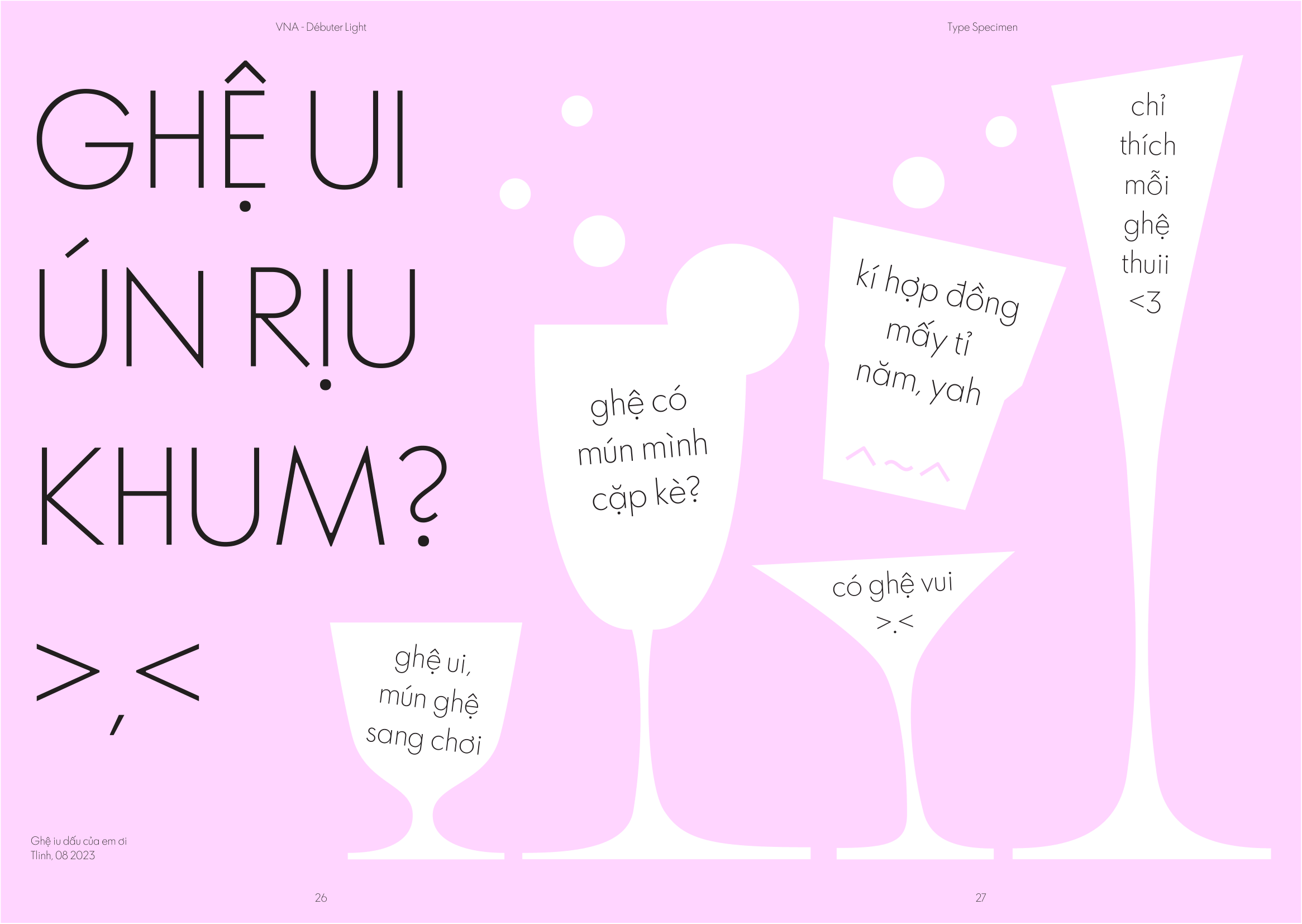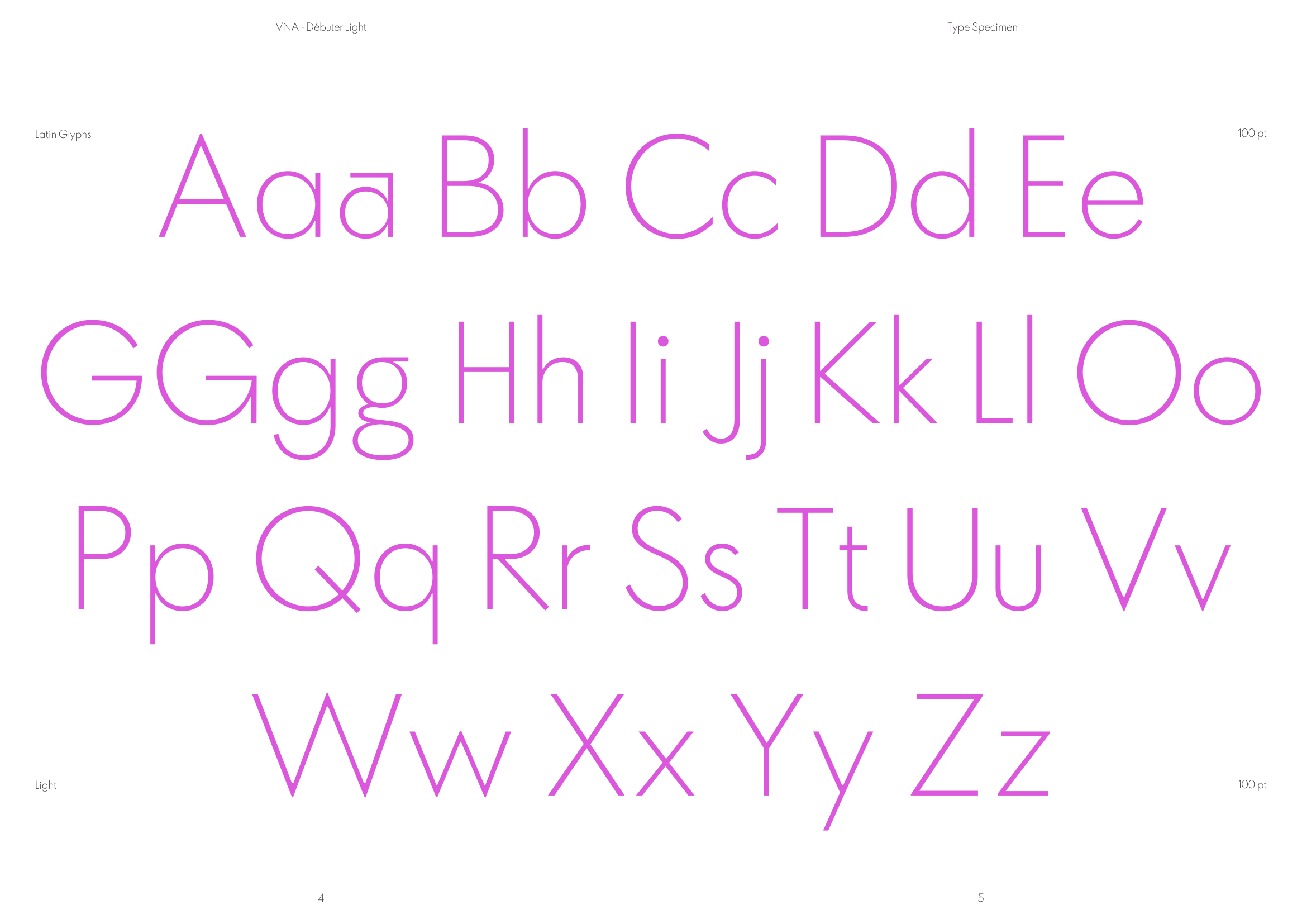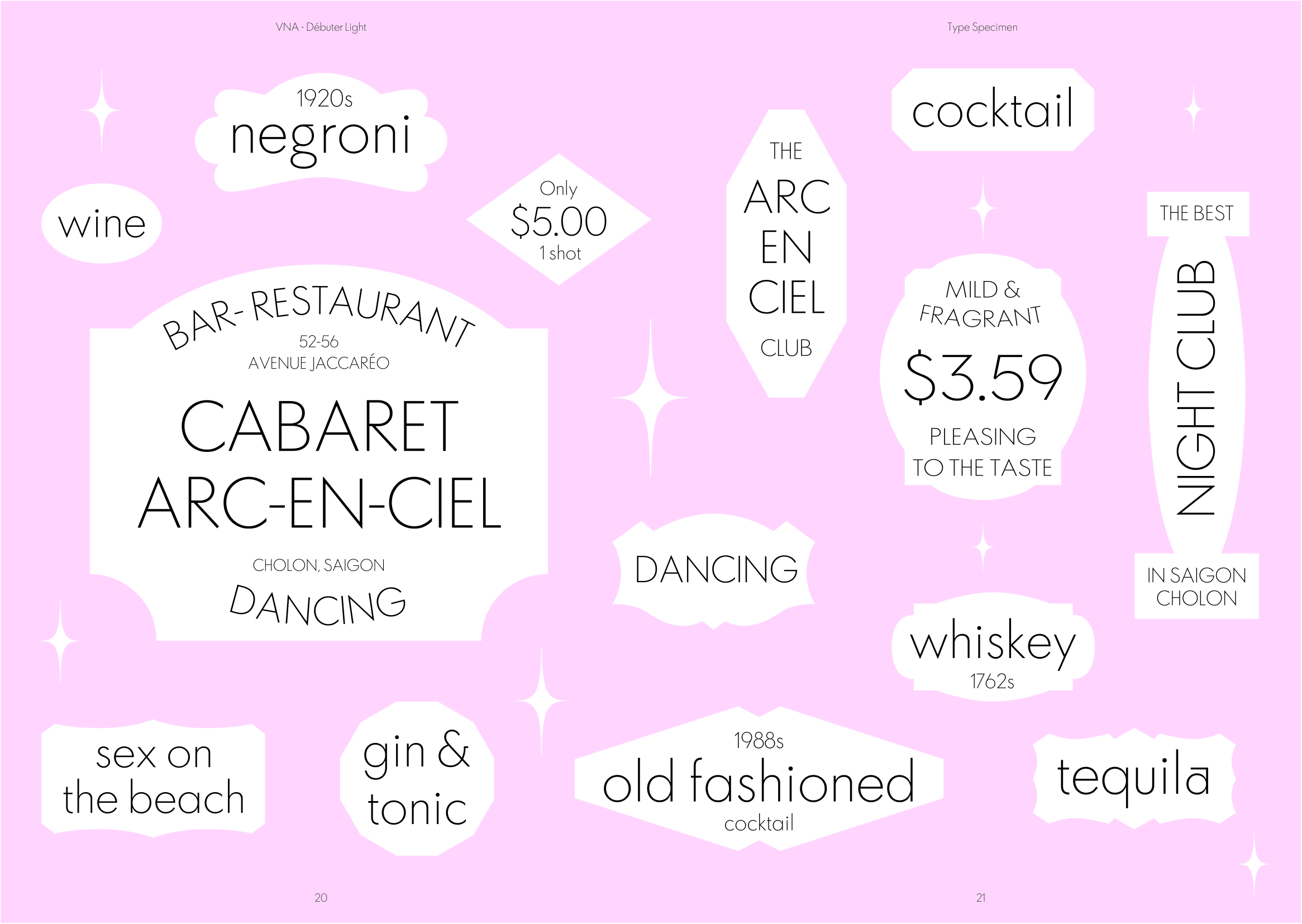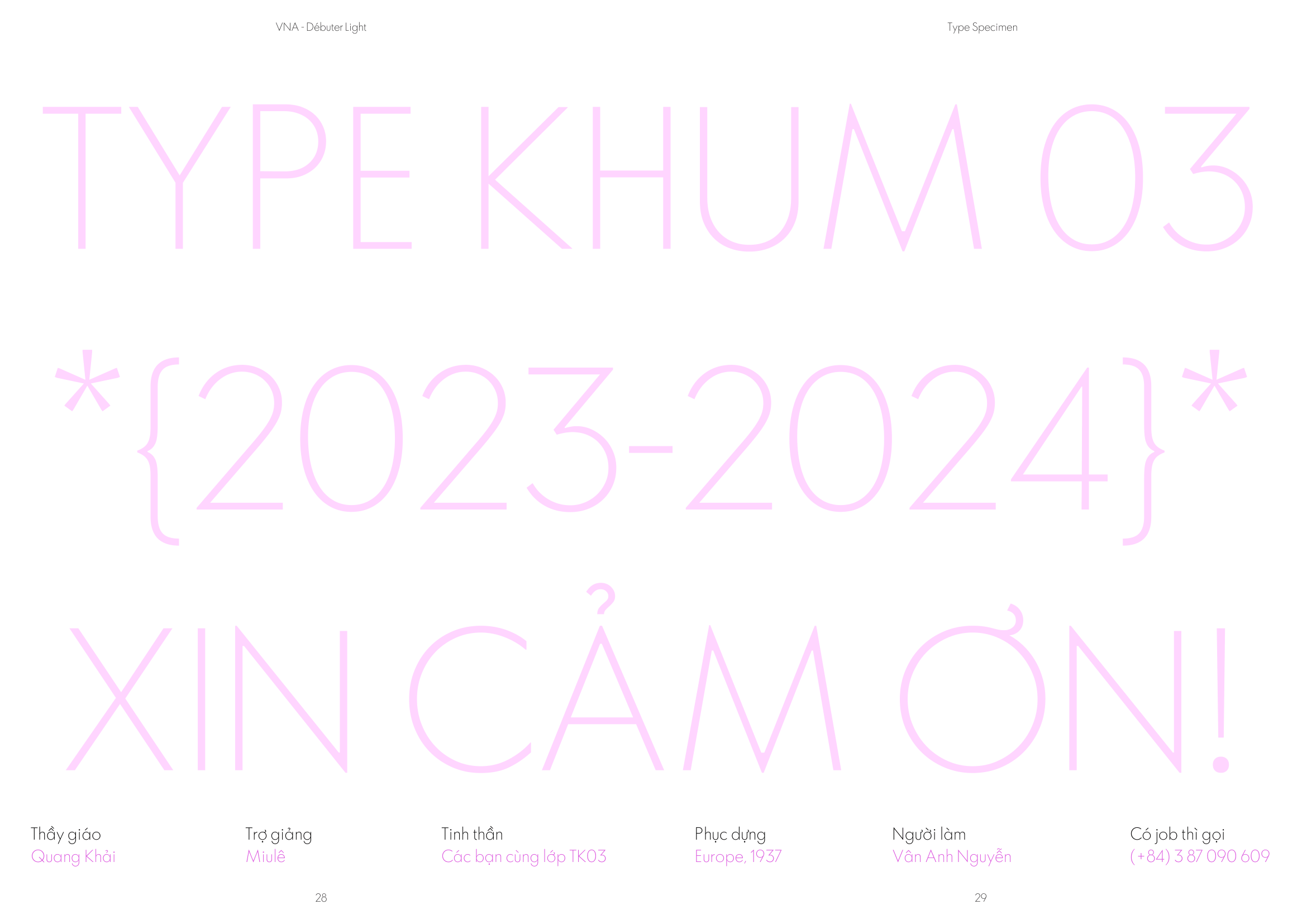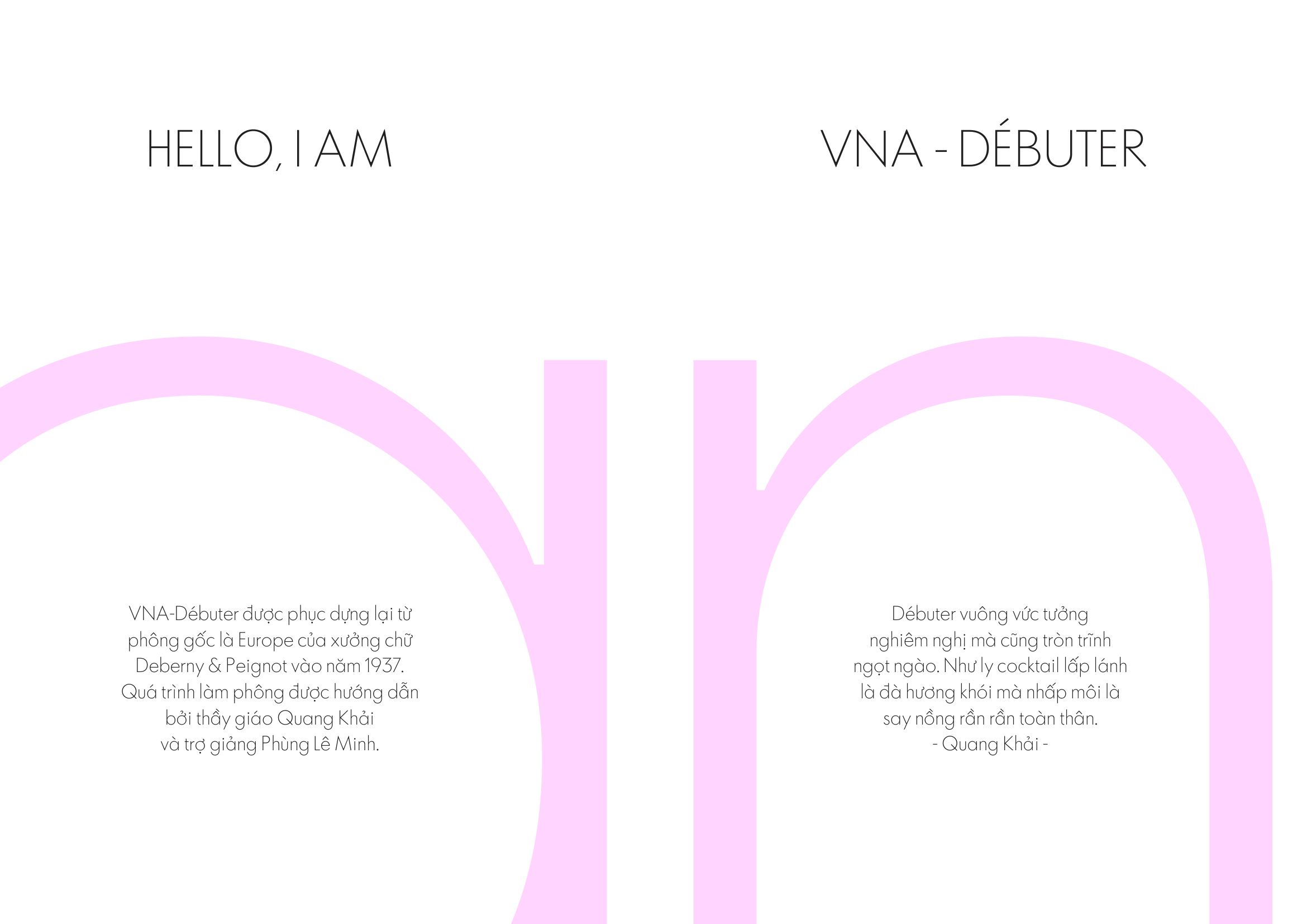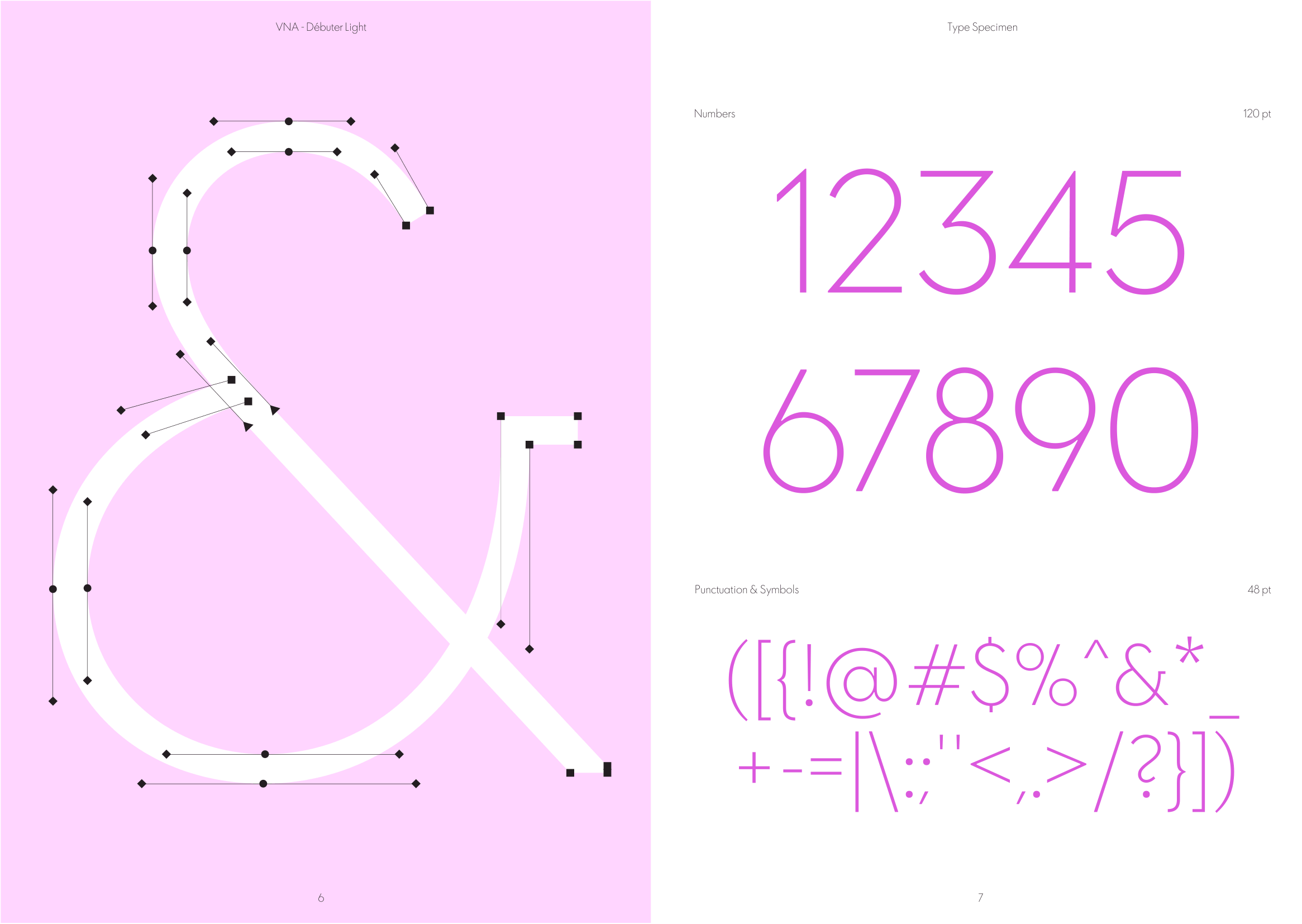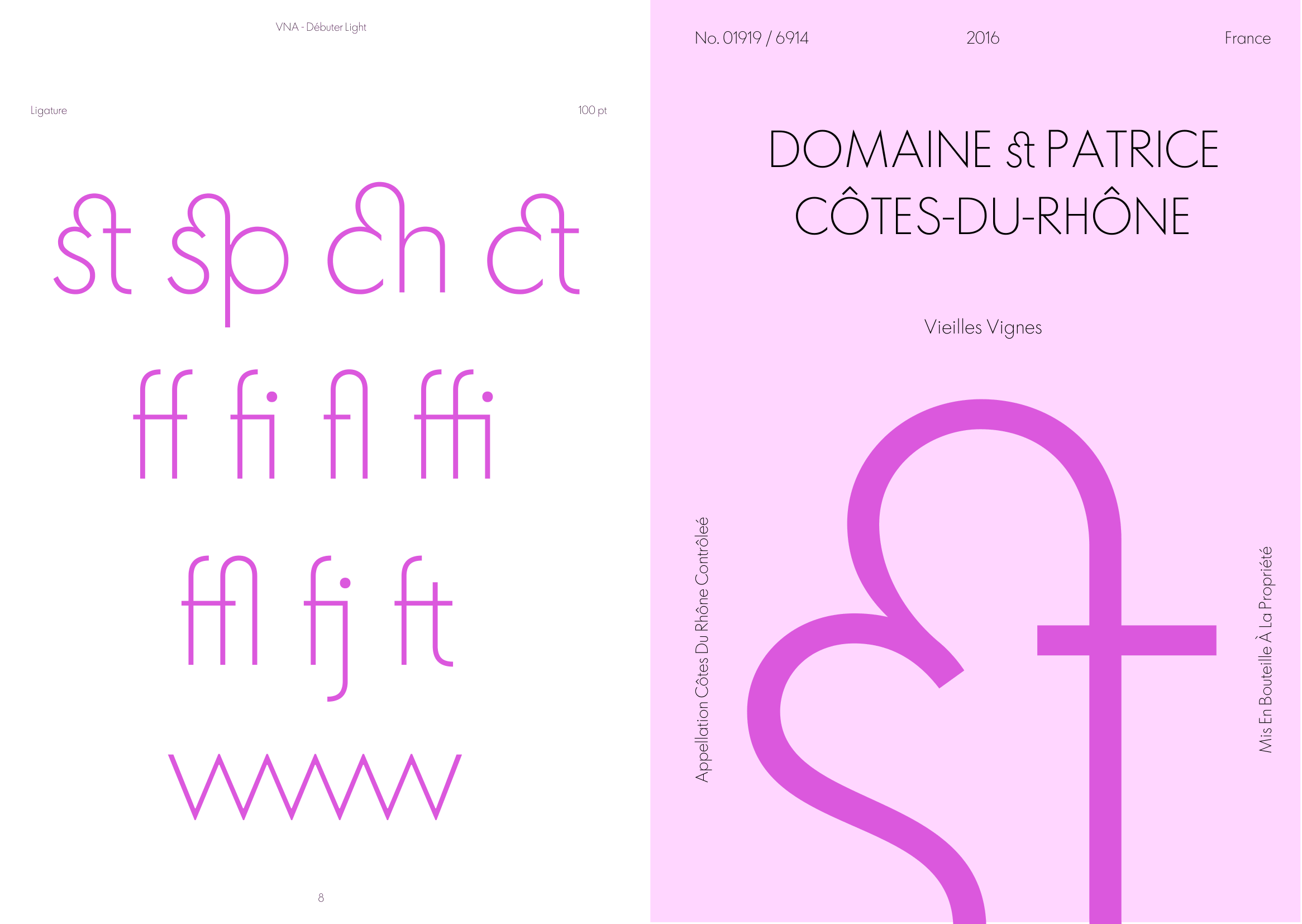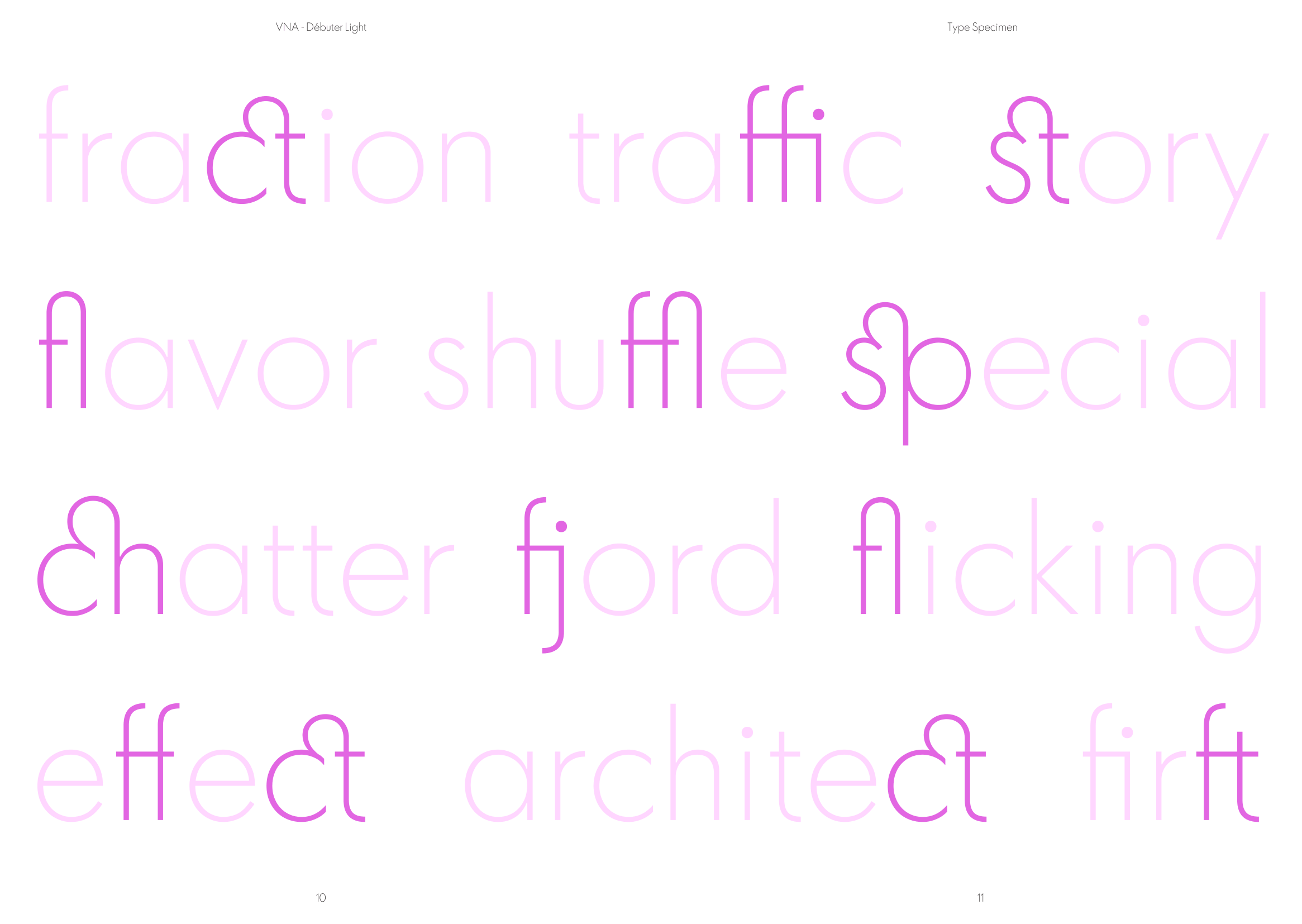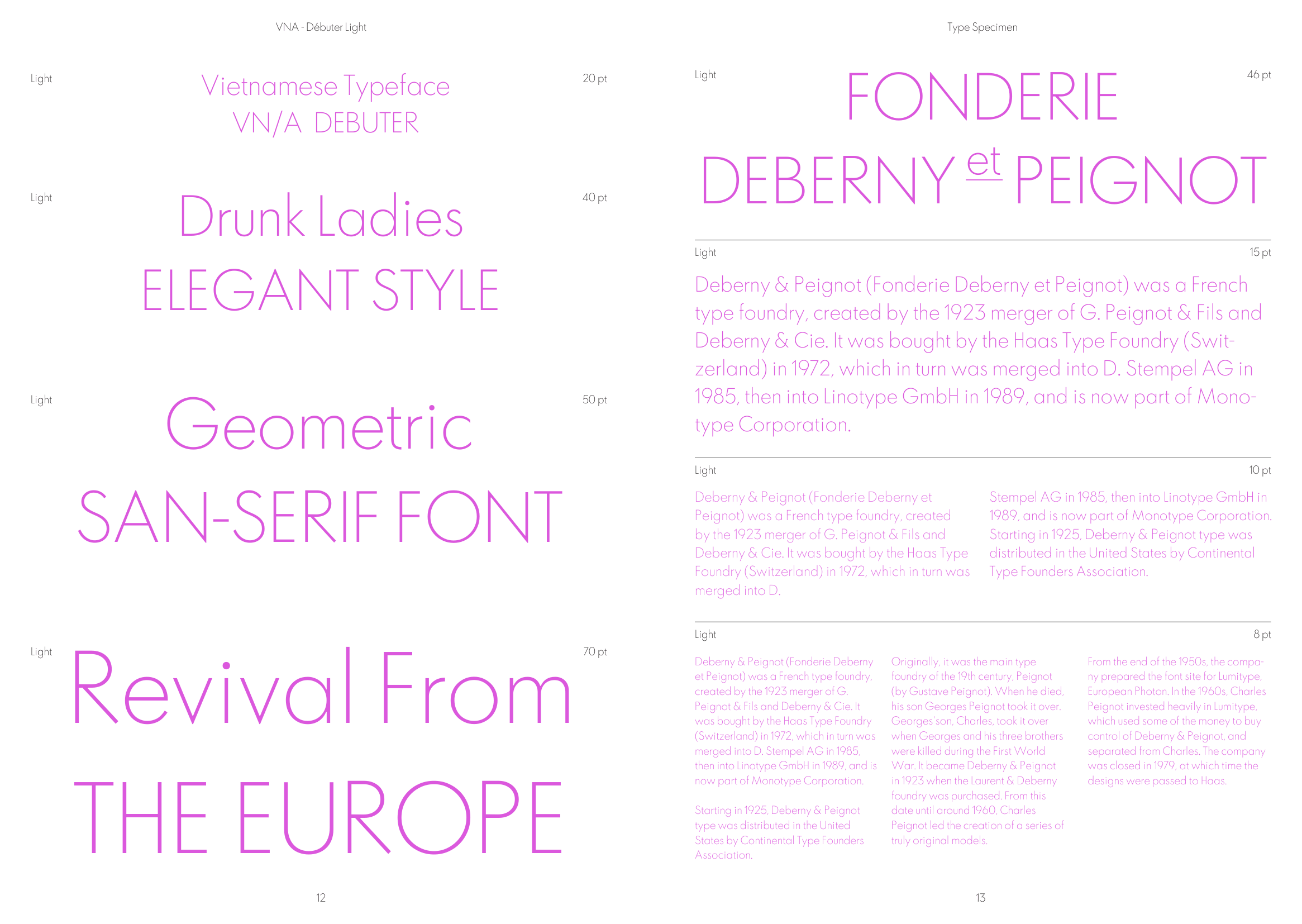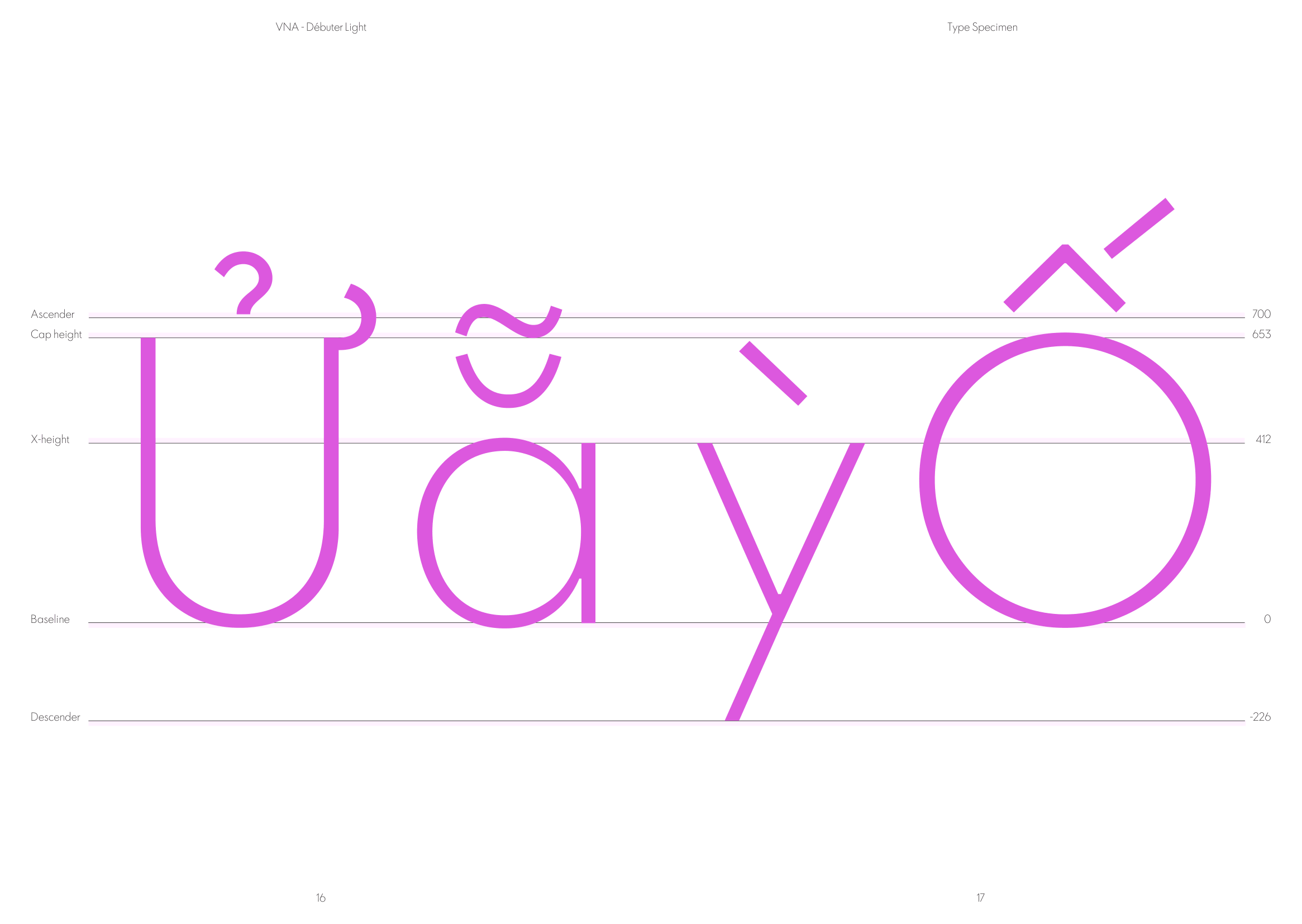
VNA Debuter
Về VNA Debuter: VNA-Débuter được phục dựng lại từ phông gốc là Europe của xưởng chữ Deberny & Peignot vào năm 1937. Débuter mỏng như sợi tóc đi từng nét mượt như kẻ thước. Débuter vuông vức tưởng nghiêm nghị mà cũng tròn trĩnh ngọt ngào. Như ly cocktail lấp lánh là đà hương khói mà nhấp môi là say nồng rần rần toàn thân.
Geometric Sans-serif
VNA Debuter
Drunk
VNA Debuter
Rượu nồng
VNA Debuter
Bar & Restaurant
VNA Debuter
Hợp đồng bàn nhậu
VNA Debuter
The launch of Europe was announced in the spring of 1930, introduced as "an antique in three weights, the most beautiful, the best developed."
VNA Debuter
By 1931, Deberny & Peignot published a dedicated showcase titled Europe et le Studio, positioning it as "the face of our time" and highlighting its particular suitability for use alongside photography. Europe/Futura held a special status in the minds of both Peignot and Vox, it was considered an excellent titling face and recommended for short texts, but was not seen as a workhorse typeface for long-form body copy. In essence, Europe represents a pivotal moment in French typographic history, the point at which the geometric modernist movement, born in Germany with the Bauhaus spirit, was formally adopted and rebranded for the French market, shaping the visual language of advertising and print throughout the 1930s.